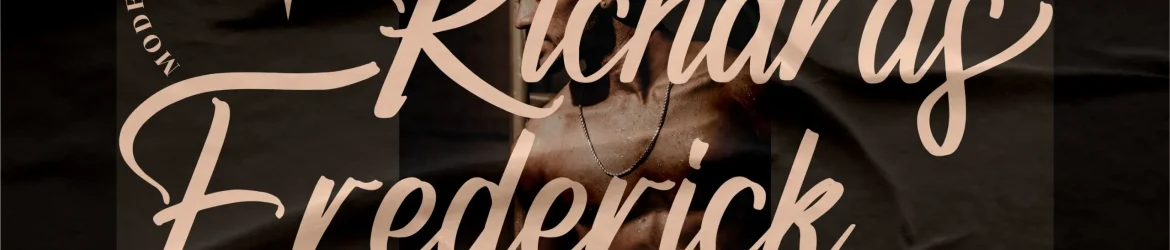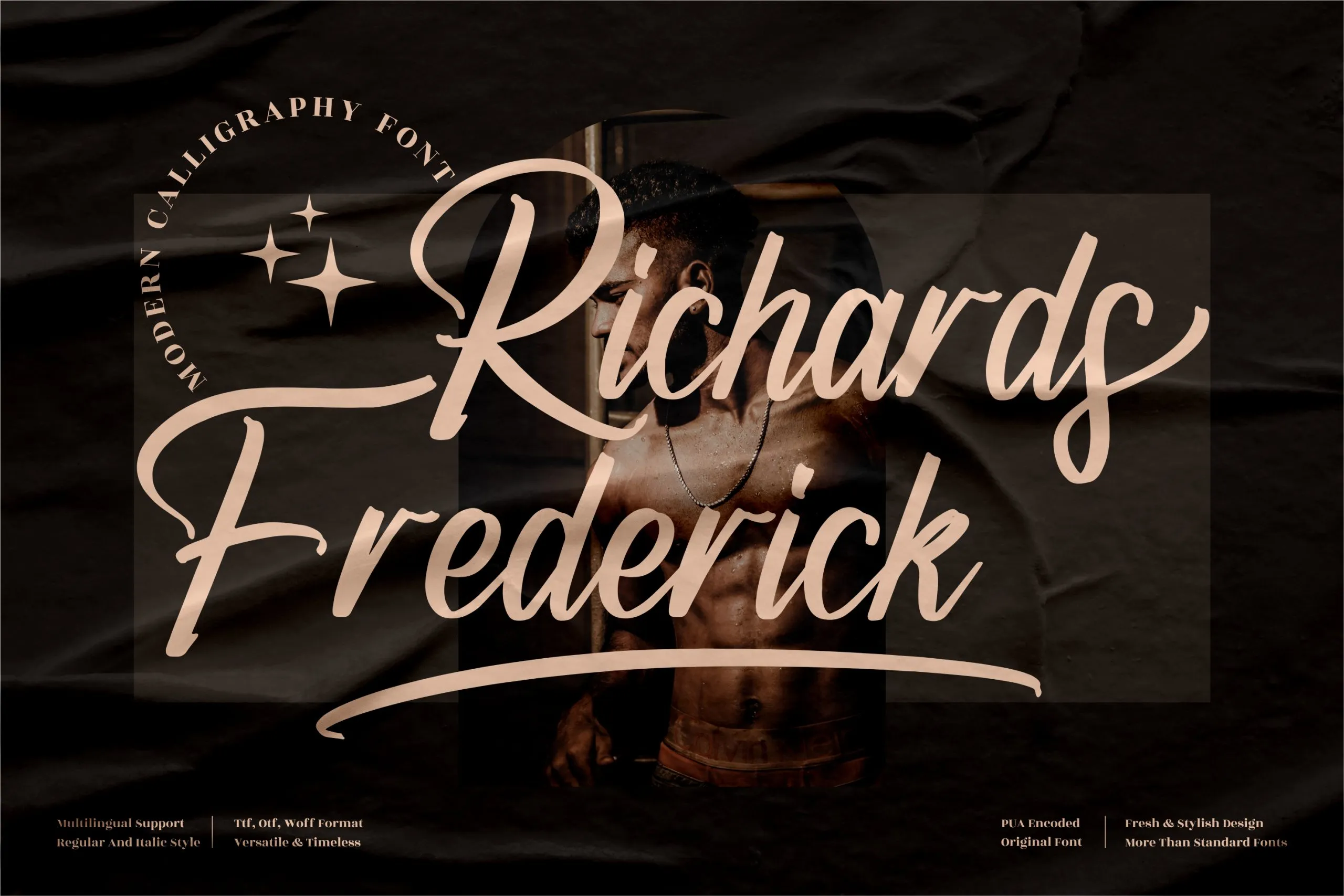
Richards Frederick Font – Fonte Grátis
Richards Frederick Font
A fonte ‘Richards Frederick’ é perfeita para qualquer projeto que exija uma assinatura única e sofisticada. Seja para criações tipográficas de logotipos, desenvolvimento de marcas, designs de mobiliário, embalagens de produtos, têxteis personalizados, cartões promocionais, capas de livros, etiquetas, impressão em fotografia ou até mesmo pacotes de presente. Seja qual seja o seu projeto, a fonte ‘Richards Frederick’ garante um toque de sofisticação e originalidade que tornará seu design destoante do resto da galeria. A sua elegância e simetria permitem uma aplicação versátil na criação de qualquer tipo de obra. Seja para cartões de nome, convites ou até mesmo cartazes de eventos especiais, a fonte ‘Richards Frederick’ garante um toque único que transforma qualquer projeto em algo extraordinário. Esta fonte é adequada tanto para quem busca uma personalização mais elaborada quanto para aqueles que valorizam uma assinatura cuidadosamente escolhida e refinada. Na categoria de fontes para escrituração, a ‘Richards Frederick’ oferece um toque autêntico que torna o seu design ainda mais especial. Este é um ótimo recurso para quem busca criar obras de arte tipográfica incrivelmente sofisticadas ou simplesmente quer dar um toque único aos seus projetos pessoais e profissionais.